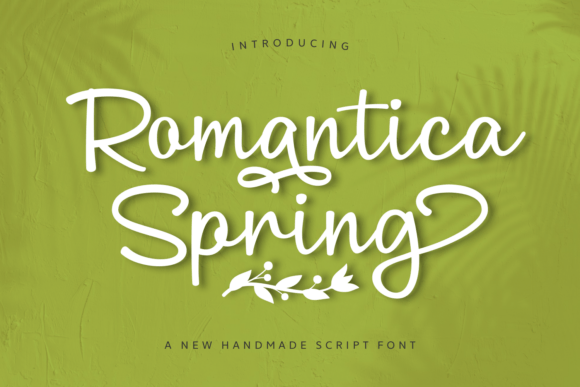
Romantica Spring
Jika Anda mencari aset berkualitas tinggi seperti Romantica Spring, paket premium ini adalah pilihan fantastis untuk proyek kreatif Anda.
Baik Anda membuat produk POD (Print on Demand), undangan pernikahan, atau grafis media sosial, Romantica Spring adalah pilihan yang sangat ideal.